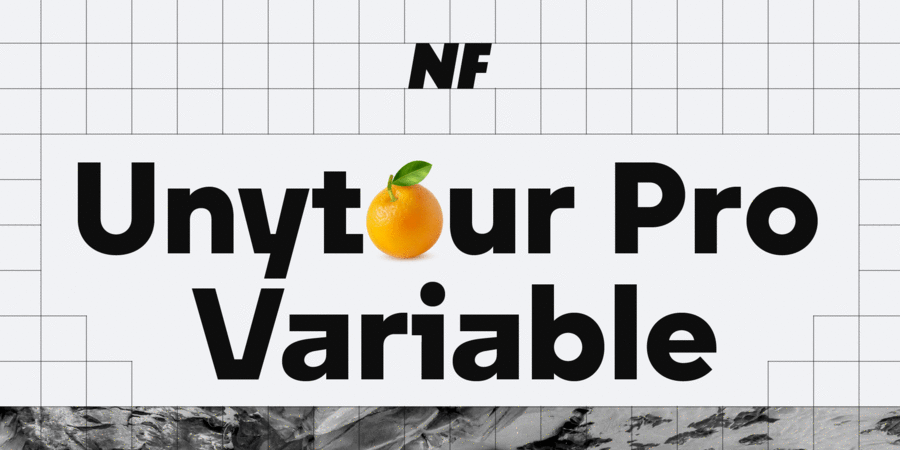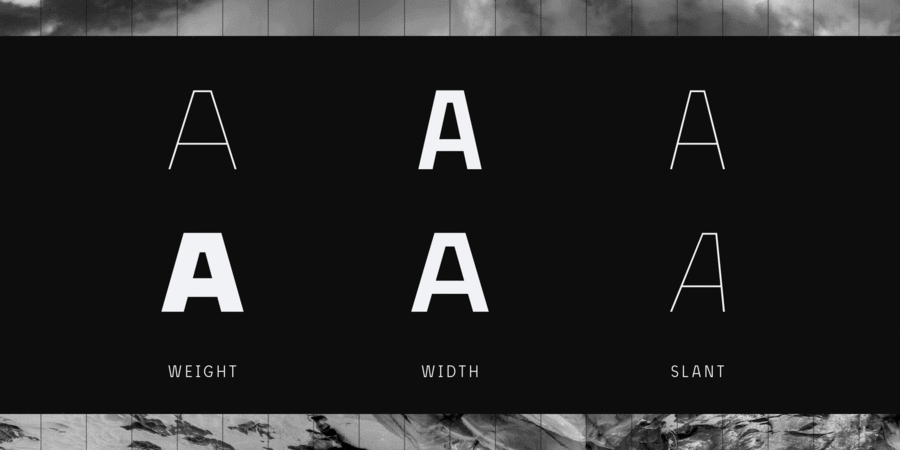
Опис шрифта Unytour Pro VariableШрифт Unytour Pro Variable – сучасне доповнення до гарнітури Unytour Pro. Варіативний шрифт містить 3 осі: Вага (Weight), Ширина (Width), Нахил (Slant). Завдяки технології варіативних шрифтів, Unytour Pro Variable надає дизайнерам гнучкість у роботі. Ви з легкістю можете налаштовувати параметри насиченості, ширини та нахилу, щоб досягти ідеального балансу та гармонії візуального стилю для свого проєкту.
Шрифт містить альтернативні гліфи для таких символів, як A, G, I, R, a, l, t, y, що додає вашій типографіці особливого характеру та індивідуальності. Крім того, багатий набір OpenType-функцій значно розширює ваші творчі можливості. Unytour Pro Variable має гарну читабельність як у друці, так і на екранах телевізорів та інших пристроях. Шрифт розробив Микола Савчук у 2024 році. Особливості сімейства шрифтів Unytour Pro VariableХіт десятиліття:
Асоціації з сімейством шрифтів Unytour Pro VariableОсобистість і характер гарнітури:
твердий, надійний, точний, впевнений, сталевий, рівний, стійкий, холодний, машинний, гострий, урбаністичний, міський, скляний, крижаний, ламаний, оригінальний, квадратний, експериментальний, дзвінкий, сміливий, кутастий, рубаний, чіткий, дивний, характерний, незвичайний, модний, цікавий, мінімалістичний